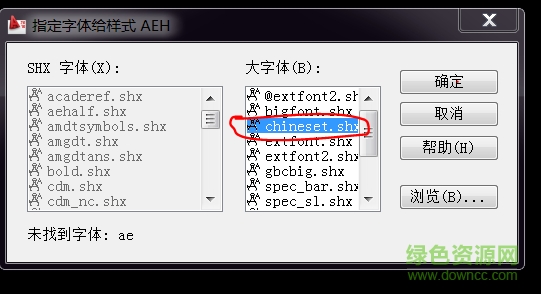
軟件介紹 軟件標簽: chineset CAD字體 chineset.shx是Auto CAD中一款繁體中文字體,全稱txt.chineset,歡迎需要的朋友來綠色資源網(wǎng)免費下載!txt.chineset介紹chineset.shx是一款cad字體,中文繁體舒服,使用簡單方便,支持大小間距調(diào)節(jié)。chineset字體安裝1.在綠色資源網(wǎng)下載并解壓2.文件為“.shx”格式,需用winrar解壓3.使用前先關(guān)閉autocad4.將字體文件復制到AutoCAD安裝目錄下面的fonts目錄里5.使用txt.chineset.shx的功能 軟件截圖 上一張下一張(1 / 1) 安裝詳細截圖 猜你喜歡 cad字體 cad字體 cad字體是AUTOCAD模型設(shè)計必備的字體包,這里為大家提供了cad字體大全 完整版,都是一些cad常用字體下載,cad字體的使用可以讓用戶在使用cad軟件時更加的得心應(yīng)手,因此裝cad字體還是很有必要的。 查看更多>> CAD pkpmchn字體 3KB/中文/0.8/下載 autocad2019字體大全 540.00M/中文/1.0/下載 sfont.shx 660KB/中文/3.3/下載 _tel_dim.shx字體 1.17M/中文/1.6/下載 mhztxt字體 35KB/中文/6.6/下載 hbsmall.shx 1.22M/中文/0.4/下載 其他版本下載 標題 大小 更新日期 下載 下載地址 電腦版 chineset字體 點擊報錯 軟件無法下載或下載后無法使用,請點擊報錯,謝謝! 關(guān)閉報錯反饋 請描述您所遇到的錯誤,我們將盡快予以修正,謝謝! *必填項,請輸入內(nèi)容 本類最新 dreamweaver字體庫 首爾南山體字體 v1.06 官方版 潮字社風云簡ttf 潮字社凌渡鯤鵬簡體字體 潮字社曾玉波手書簡字體 微博慧心字體 相關(guān)文章 用CMailServer打造郵件服務(wù)器 Linux 防火墻配置基礎(chǔ)篇 cad字體庫安裝_AutoCad字體庫安裝教程 用asp處理access數(shù)據(jù)庫 設(shè)置和取消ACCESS數(shù)據(jù)庫密碼 將SQL Server2005數(shù)據(jù)庫還原或恢復到SQL Server2000數(shù)據(jù)庫中 用戶評論 熱門評論 最新評論 發(fā)表評論 查看所有評論(0) 昵稱: 請不要評論無意義或臟話,我們所有評論會有人工審核. 字數(shù): 0/500 (您的評論需要經(jīng)過審核才能顯示)